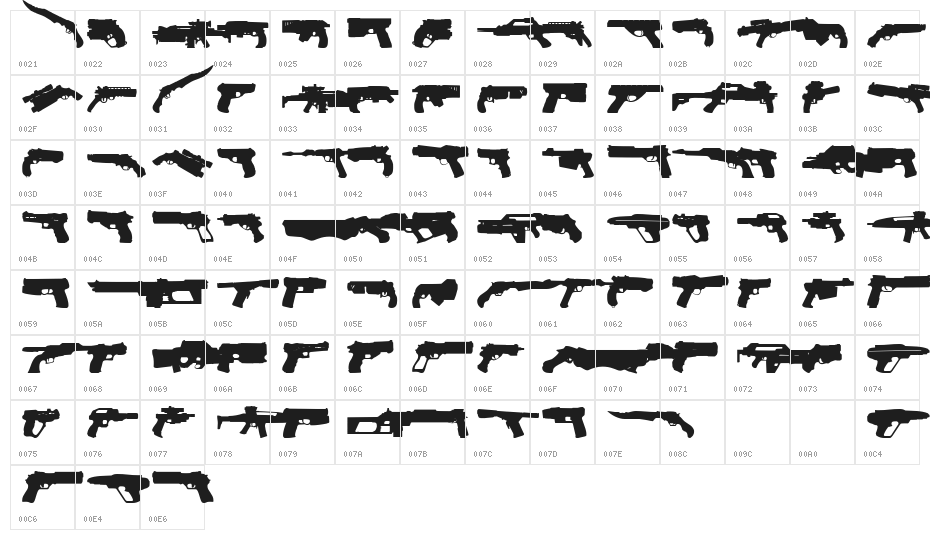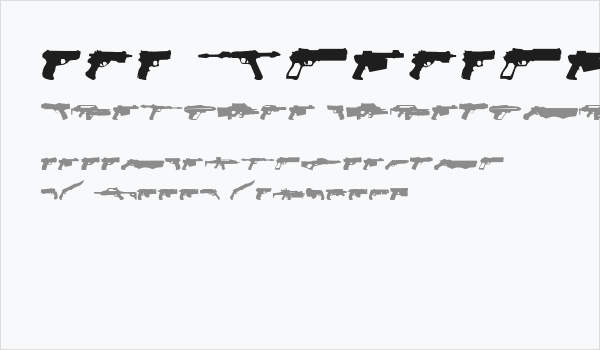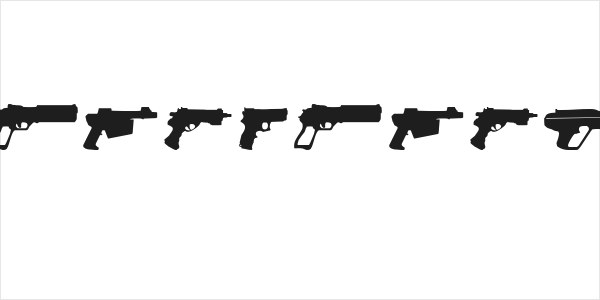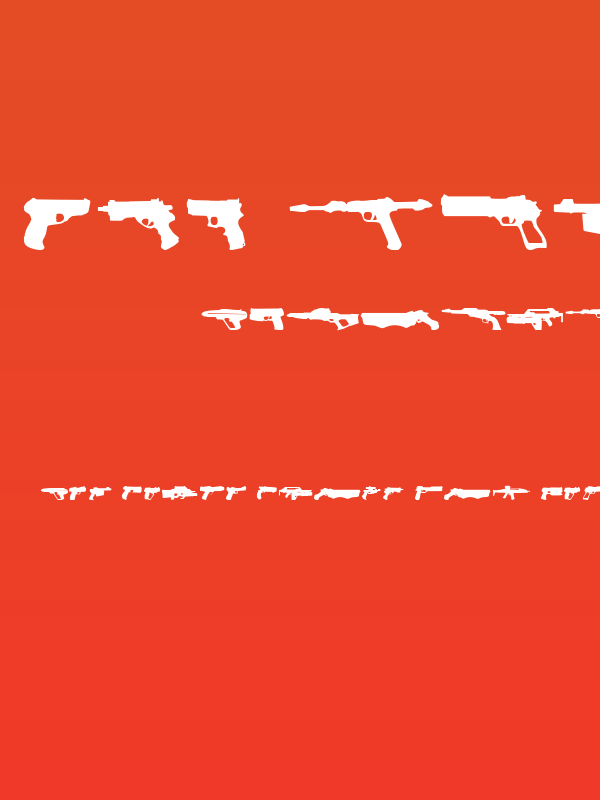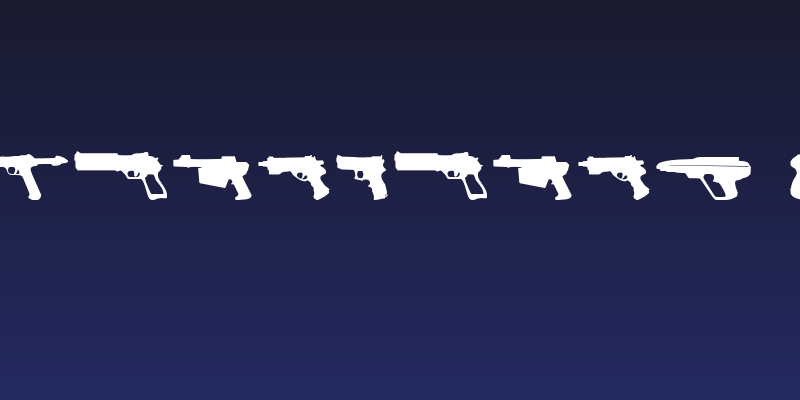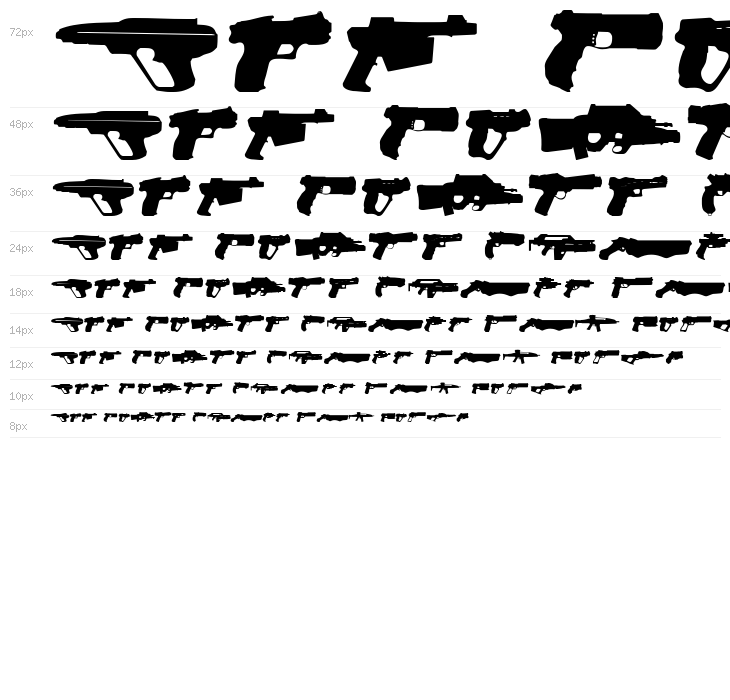
2nd Amendment 2050 Font
| 整体风格 | Decorative, Thematic, Novelty |
| 使用场景 | Logos, Posters, Themed Headlines, Event Graphics |
| 推荐项目 | Posters, themed event graphics, video game titles, protest art, novelty merchandise, or any project requiring a bold, provocative visual statement. |